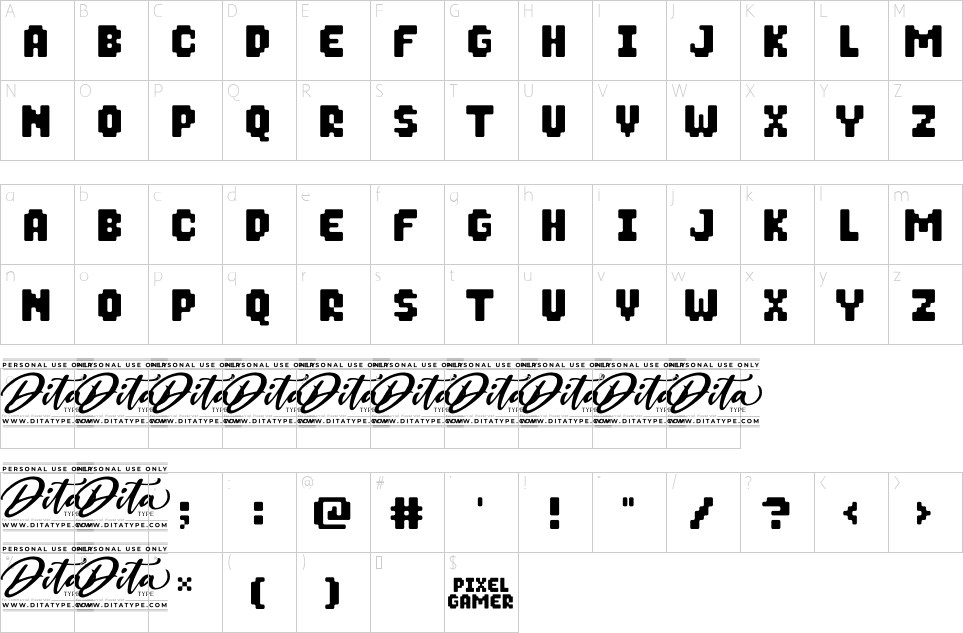
A Pixel Gamer é uma fonte de graça que oferece um estilo retrô e enérgico, perfeito para adicionar um toque de jogos de videogame em seus projetos. Desenvolvida pela Dita Type, essa fonte tem sido uma escolha popular para designers que buscam uma maneira de personalizar seu trabalho com um design minimalista e colorido. Para quem busca uma fonte que combine modernidade e nostalgia, a Pixel Gamer é uma excelente escolha. Disponível tanto para Windows quanto para Mac, a Pixel Gamer é uma fonte grata que certamente adicionará um toque único a qualquer projeto. Com mais de 1.748 downloads, é fácil ver por que essa fonte é tão valorizada pelos designers.